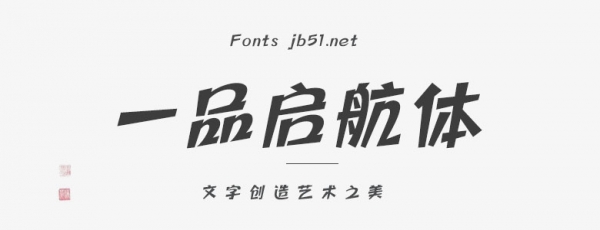
“一品啟航體”以中國傳統(tǒng)書法為根基,融入現(xiàn)代設(shè)計(jì)美學(xué),字形遒勁昂揚(yáng),筆鋒充滿動(dòng)勢,象征著一品威客銳意進(jìn)取、勇立潮頭的品牌內(nèi)核。作為公益字體,其將廣泛應(yīng)用于文化傳播、公益宣傳、商業(yè)設(shè)計(jì)等領(lǐng)域,旨在成為連接你我、傳遞正能量的橋梁,激勵(lì)更多人勇敢追夢,共創(chuàng)美好未來。
夢想、青春、創(chuàng)意,是“一品啟航體”的標(biāo)簽。作為一品威客納斯達(dá)克上市紀(jì)念公益字體,其在字形特征、字形結(jié)構(gòu)、筆畫設(shè)計(jì)等方面呈現(xiàn)諸多亮點(diǎn),體現(xiàn)了傳統(tǒng)與現(xiàn)代的交融。
中宮舒展,識(shí)別度高。字體采用中宮舒展設(shè)計(jì),擴(kuò)大字面率,兼具傳統(tǒng)書法結(jié)構(gòu)美學(xué)與現(xiàn)代閱讀習(xí)慣,視覺張力與辨識(shí)度并存。
動(dòng)感外框,剛?cè)岵?jì)。平行四邊形外框賦予字體強(qiáng)烈方向感,呼應(yīng)“啟航”主題;筆畫轉(zhuǎn)折處巧妙融入弧度,剛毅中透出溫度,傳遞企業(yè)“銳意進(jìn)取中不失人文關(guān)懷”的理念。
動(dòng)態(tài)筆觸,靈動(dòng)鮮活。模擬真實(shí)書寫壓感,線條粗細(xì)變化自然,斷筆處理營造呼吸韻律,打破傳統(tǒng)字體靜態(tài)平衡,展現(xiàn)品牌開放發(fā)展的創(chuàng)新基因。